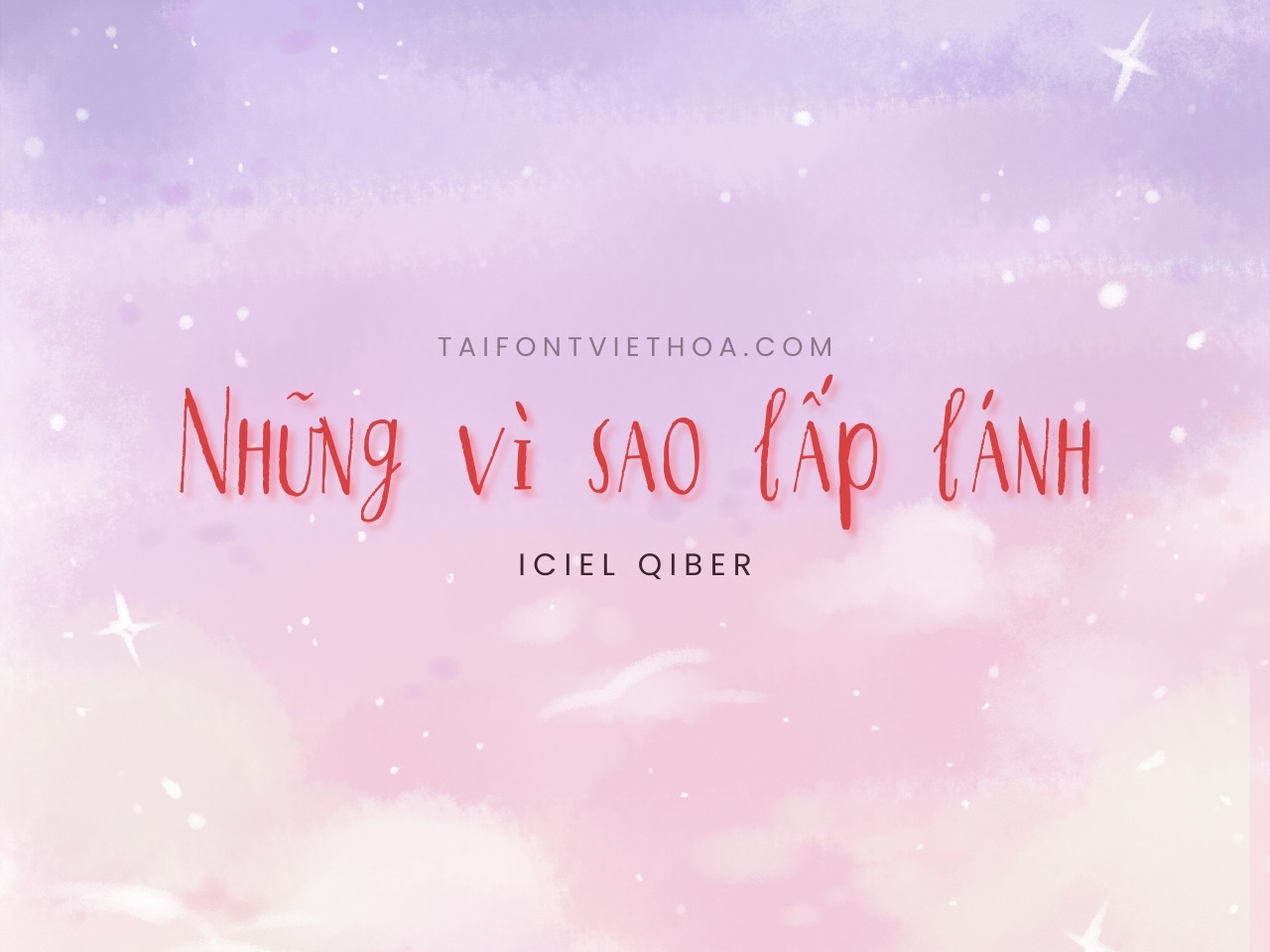
Giới thiệu về font iCiel Qiber – Cá tính, đậm chất thủ công và đầy năng lượng
iCiel Qiber là một kiểu chữ viết tay mang tính nghệ thuật cao, được thiết kế theo phong cách condensed handwritten (viết tay cô đọng) với đường nét gãy gọn, mạnh mẽ. Phiên bản Việt hóa do iCiel thực hiện, hỗ trợ đầy đủ tiếng Việt cùng hơn 60 ngôn ngữ khác, giúp font trở thành công cụ lý tưởng cho các nhà thiết kế cần tạo ra dấu ấn cá nhân trong thiết kế đồ họa.
Đặc điểm thiết kế và ứng dụng của font iCiel Qiber
iCiel Qiber được xây dựng với tỷ lệ hẹp (condensed), các ký tự cao và gọn, tạo cảm giác tiết kiệm không gian nhưng vẫn đảm bảo độ rõ ràng. Các nét viết tay được giữ lại sự tự nhiên của stroke bút thật, đi kèm với một chút “thô ráp” giúp font không bị quá hoàn hảo, tăng tính chân thực và cá tính riêng. Font còn hỗ trợ ligatures và alternate glyphs để người dùng tùy biến bố cục sáng tạo.
Font này phù hợp cho các ứng dụng như: thiết kế bao bì handmade, poster sự kiện nghệ thuật, typography truyền cảm hứng, bìa sách sáng tạo, hoặc logo thương hiệu mang phong cách vintage – thủ công – đường phố. Ngoài ra, iCiel Qiber còn rất phù hợp trong lĩnh vực quảng cáo ẩm thực, café, quán ăn sáng tạo hoặc các dự án thiết kế cho cộng đồng trẻ, năng động và cá tính.